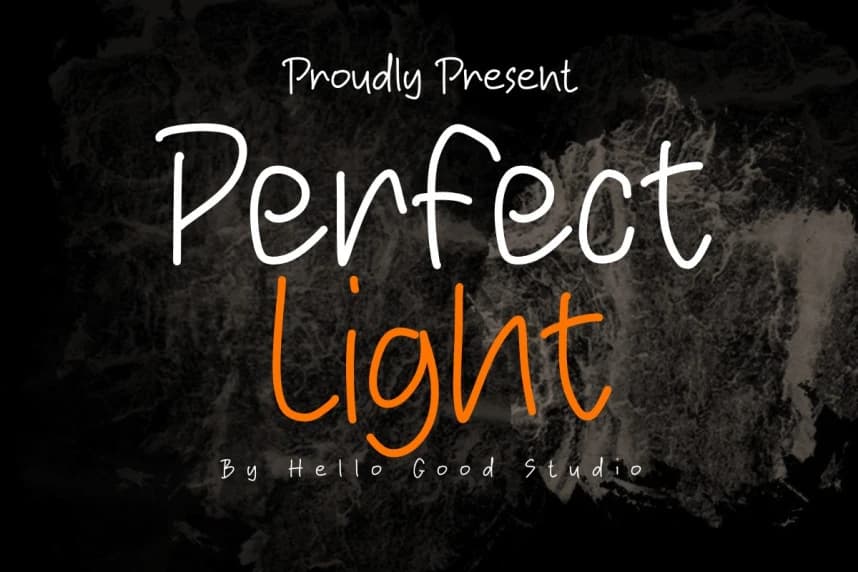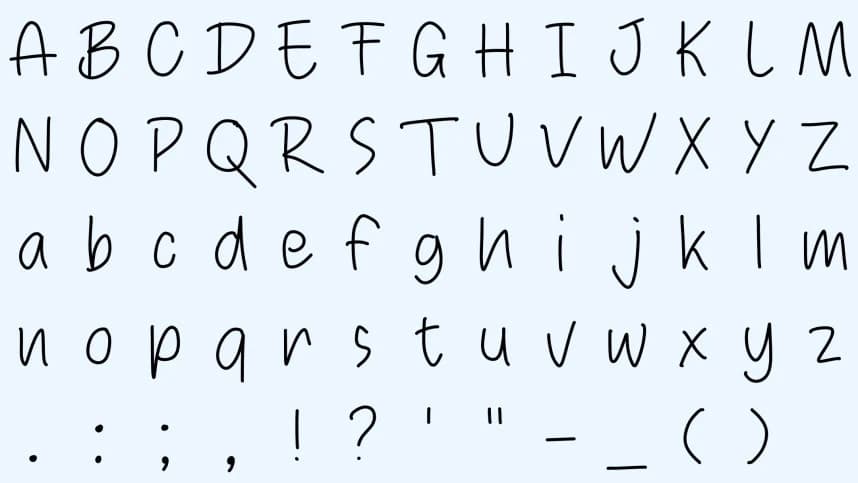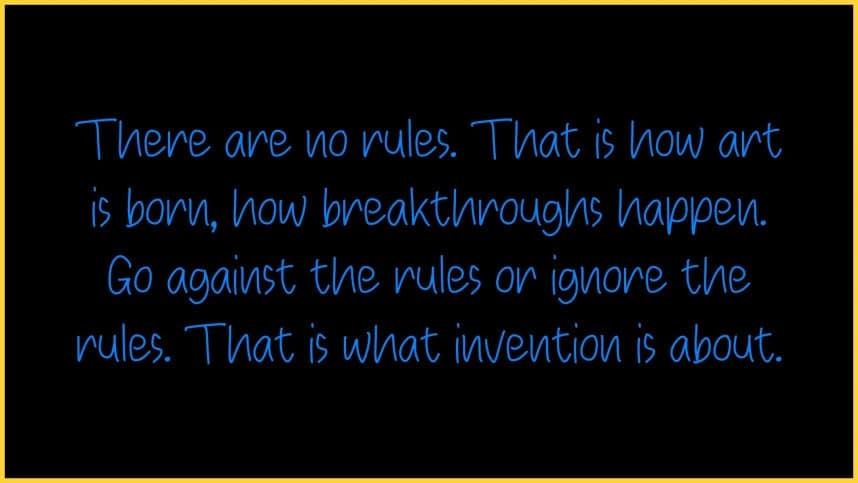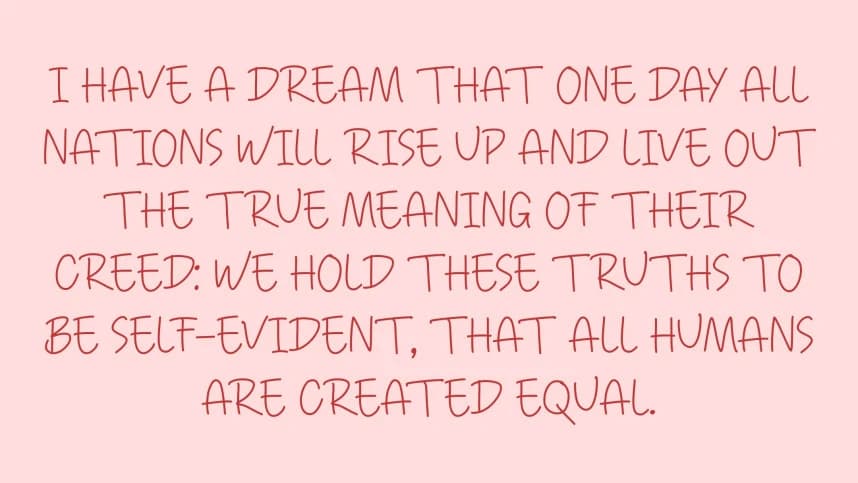
Perfect Light Font
Perfect Light Font, temiz ve zarif minimalist bir stile sahip ince bir el yazısı fontudur. İnce, akıcı çizgilere sahip ve doğal olarak aralıklı harf hatlarıyla bu font, yumuşak, havadar ve kişisel bir his yaratır.
Perfect Light Font, temiz ve zarif minimalist stile sahip narin bir el yazısı fontudur. İnce, akıcı çizgiler ve doğal olarak aralıklı harf biçimleriyle bu font, yumuşak, havadar ve kişisel bir his yaratır.